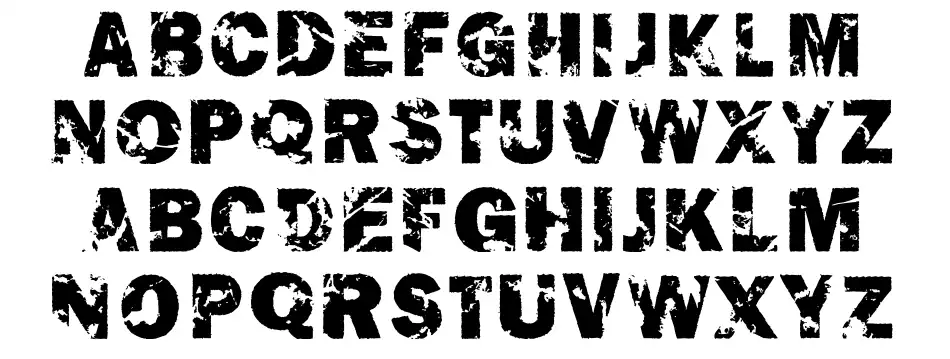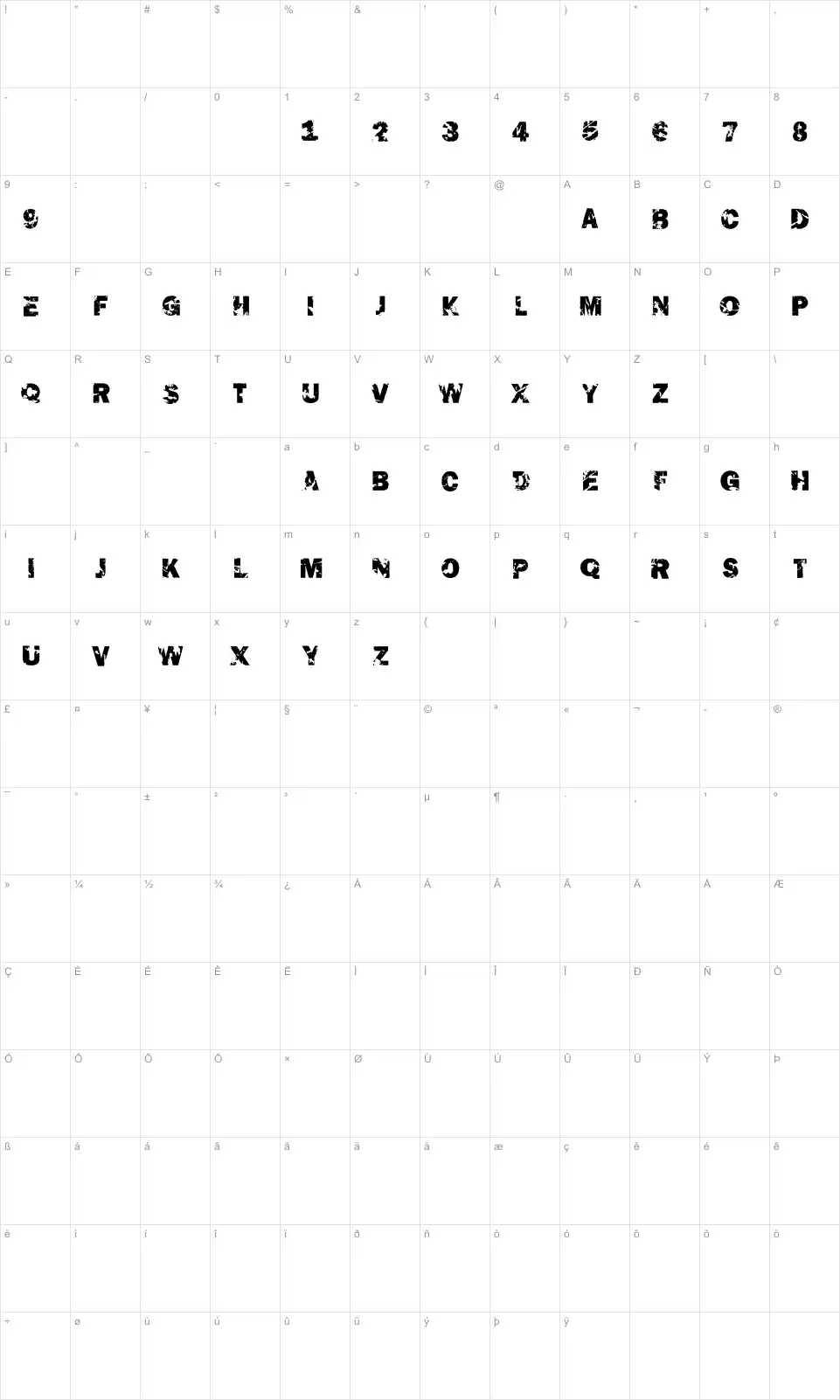
A fonte The End Font, criada por Robert Friedrich, está disponível para download na categoria de ‘Fancy’, classificada como ‘Destroy’, um termo que remete à forma agressiva e poderosa que essa fonte adquire. Se você está à procura desta fonte especializada em efeitos chamativos, Robert Friedrich oferece a opção de baixar em formato TTF, o que permite a personalização de mensagens antes de utilizá-la. Desde sua adição em 12 de julho de 2022, a fonte The End Font já foi baixada milhares de vezes, demonstrando seu valor como uma fonte criativa e única. Com 184 KB de tamanho, ela é uma escolha prática para qualquer projeto que necessite de uma fonte imponente e diferenciada. Para mais informações e para acessar diretamente o trabalho do designer, visite o site oficial de Robert Friedrich: http://robapexenterprise.wix.com/robert-friedrich.
Categoria: Fancy › Destroy